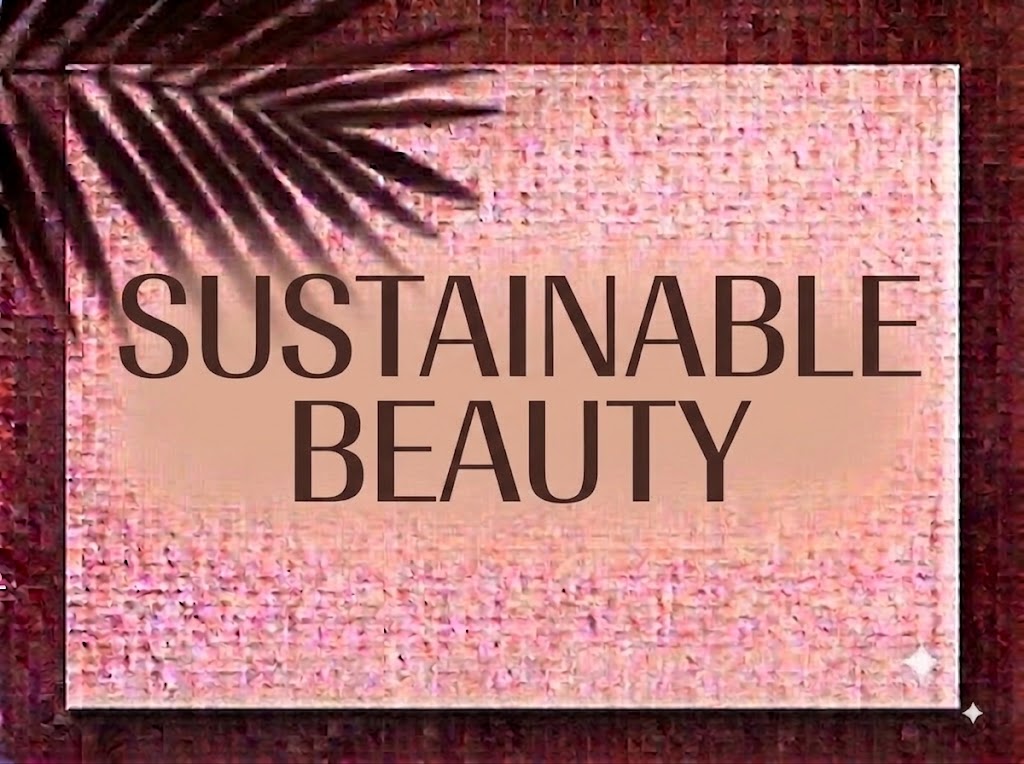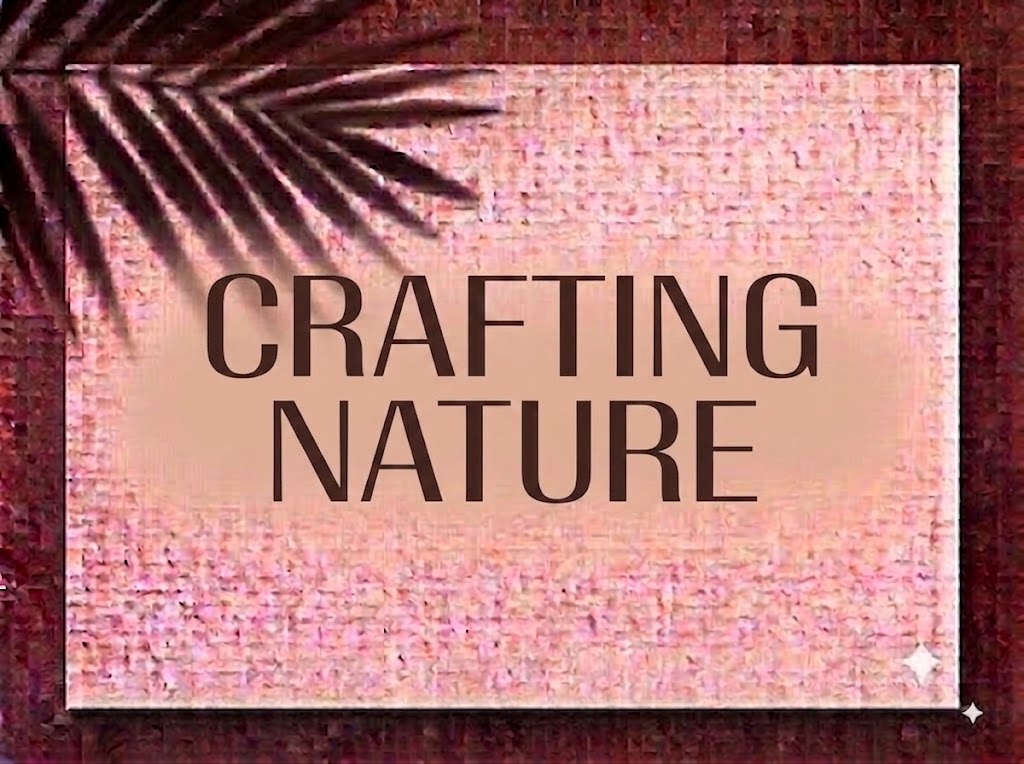
1FTV Ranoya
Trong xu hướng thiết kế đồ họa đương đại, những bộ phông chữ không chân hiển thị (Display Sans-Serif) mang phom dáng cao ráo kết hợp cùng các đường bo vát góc nghệ thuật luôn tạo nên dấu ấn thị giác độc bản. Sự pha trộn giữa cấu trúc hình học gọn gàng và những nét cong bất đối xứng mang lại hơi thở hiện đại, đậm chất công nghệ, thời trang và tương lai (futuristic).
Nếu bạn đang tìm kiếm một phông chữ hiển thị hiện đại, phá cách để làm poster sự kiện, bìa lookbook thời trang, banner công nghệ hay tiêu đề video ngắn bắt mắt, font 1FTV Ranoya chính là sự lựa chọn không thể bỏ qua.
Giới thiệu về font 1FTV Ranoya
Font 1FTV Ranoya là bộ chữ hiển thị không chân mang phong cách Modern Display Sans, nổi bật với sự kết hợp giữa dáng chữ thon cao và các chi tiết bo vát tinh xảo:
Tên phông chữ: 1FTV Ranoya
Đặc điểm nổi bật của phong cách thiết kế Ranoya
Sức hút thị giác của font 1FTV Ranoya đến từ tỷ lệ chữ cân đối cùng những đường cắt nét đầy tính sáng tạo:
Phom dáng thon cao (Condensed/Tall Display): Tỷ lệ chiều cao nổi bật giúp các dòng tiêu đề chiếm trọn không gian theo chiều dọc mà vẫn giữ được độ thoáng, tiết kiệm diện tích chiều ngang tối ưu cho các bố cục hạn chế không gian.
Chi tiết vát góc & vòm cong bất đối xứng: Điểm đắt giá nhất của phông chữ nằm ở các đường cong vòm mượt mà kết hợp các góc vát dứt khoát ở các ký tự như
m,n,r,u,h,k,x,a,b,d,g,p,q. Chi tiết này mang lại vẻ đẹp tân tiến, sắc sảo và đậm chất thời thượng. -
Đồng bộ trọn vẹn bộ chữ và chữ số: Bộ chữ hoa kiên cố kết hợp liền mạch cùng dàn chữ thường mềm mại và hệ thống chữ số 0-9 phom dáng độc đáo, giúp bạn dễ dàng phân tầng nội dung cho mọi tác phẩm thiết kế.
Khoảng cách giữa các chữ (kerning) và tracking được tính toán chuẩn xác, giúp các đường nét góc cạnh khi đứng liền kề không bị dính nét hay gây rối mắt.
Tích hợp trọn vẹn bộ chữ cái hoa – thường, dãy chữ số 0-9 cùng hệ thống ký tự đặc biệt, dấu câu thông dụng.
Bản Việt hóa chuẩn chỉnh giúp bạn hoàn toàn yên tâm thiết kế các văn bản tiếng Việt có dấu phức tạp mà không gặp lỗi nhảy font hay mất ký tự.
Hình ảnh demo thực tế của font 1FTV Ranoya
Khả năng hiển thị của phông chữ này được tối ưu rất tốt trên nhiều tỷ lệ kích thước khác nhau:
Kích thước nhỏ (12pt – 24pt): Cấu trúc chữ rõ ràng giúp các khối văn bản ngắn và dãy số vẫn hiển thị rành mạch trên giao diện màn hình di động.
Kích thước lớn (36pt – 72pt): Đây là đất diễn hoàn hảo nhất để 1FTV Ranoya phô diễn toàn bộ vẻ đẹp hiện đại, sắc nét của các đường bo vát góc, tạo tác động thị giác mạnh mẽ cho các dòng headline chính.
Ứng dụng trong thiết kế đồ họa và làm video
Sở hữu nét cá tính sắc sảo và hiện đại, font 1FTV Ranoya mở ra không gian ứng dụng vô cùng phong phú:
Video ngắn (TikTok, Reels, Shorts): Dáng chữ cao ráo hiển thị rất thu hút trên khung hình đứng tỷ lệ 9:16. Cực kỳ ăn nhập với các video vlog thời trang street style, review đồ công nghệ, âm nhạc điện tử (EDM/Phonk) hay clip điện ảnh.
Ảnh thu nhỏ YouTube (Thumbnail): Lựa chọn tuyệt vời cho các kênh về Tech, AI, Gaming, Thiết kế hay Lifestyle nhờ diện mạo hiện đại và gây ấn tượng mạnh.
Thiết kế Poster, Bìa Lookbook & Album: Hoàn hảo cho các poster sự kiện âm nhạc, triển lãm nghệ thuật đương đại, bìa tạp chí thời trang, lookbook và poster phim ảnh.
Nhận diện thương hiệu Tech & Fashion: Thích hợp làm logo dạng chữ, bao bì sản phẩm công nghệ, nhãn mác quần áo streetwear hay banner quảng cáo kỹ thuật số.